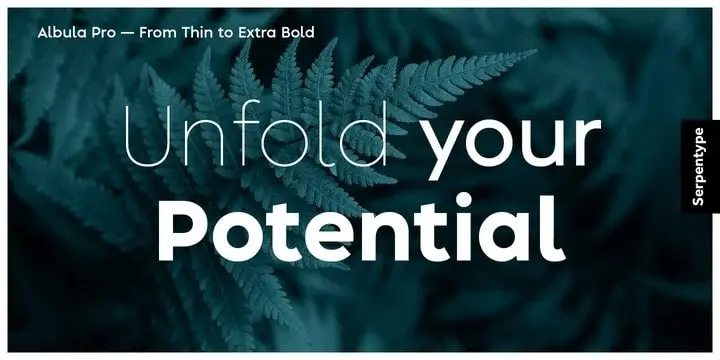
A Albula Pro Sans Serif Font é uma família de fontes que criou Serpentype, com um moderno toque ao adicionar leveza geométrica e um ar fresco à sua estética grotesca, humanista. Esta fonte sans-serif traz à vida qualquer projeto digital com seu design clean e equilibrado. Não se trata apenas de uma fonte, mas de uma maneira de dar visibilidade a ideias e designs que precisam ser percebidos, entendidos e difundidos. Seja para o design gráfico, publicidade online ou mesmo para uso em redes sociais, Albula Pro oferece um tom elegante e moderno sem perder sua identidade única. Composta de uma variedade de estilos e tamanhos, a fonte Albula Pro é perfeita para qualquer projeto que desejou transmitir ao público.